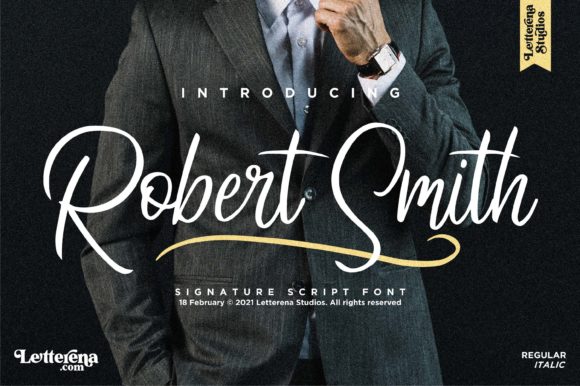
[Creativefabrica] Robert Smith Font
Роберт Смит - стильный и элегантный рукописный шрифт, готовый произвести впечатление на вашу аудиторию и придать блеск вашему брендингу. Сделайте ваши проекты выделяться с этим элегантным и замечательным шрифтом, где бы вы ни использовали его. Идеально подходит для заголовков, логотипов, рекламы, печатных цитат, упаковки и даже для брендинга вашего сайта или социальных сетей.